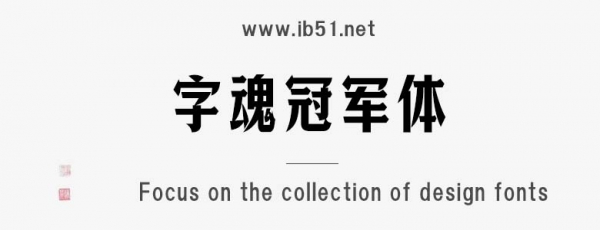
字魂冠軍體是由字魂字庫(kù)推出的創(chuàng)意字體,該字體包含7144個(gè)中文、字母、 符號(hào)和數(shù)字,具有時(shí)尚的風(fēng)格,適合應(yīng)用于藝術(shù)設(shè)計(jì)、平面宣傳設(shè)計(jì)、網(wǎng)頁(yè)設(shè)計(jì),書(shū)法字帖等領(lǐng)域。
字魂冠軍體字體是一款商用的創(chuàng)意字體,該字體包含7144個(gè)中文、字母、 符號(hào)和數(shù)字,具有時(shí)尚的風(fēng)格,可以滿足您設(shè)計(jì)上的各種需求,該字體主要用于公益宣傳等場(chǎng)景, 您不但可以在字魂網(wǎng)下載字魂冠軍體字體,同時(shí)還有眾多毛筆書(shū)法字體、創(chuàng)意字體等可供選擇!